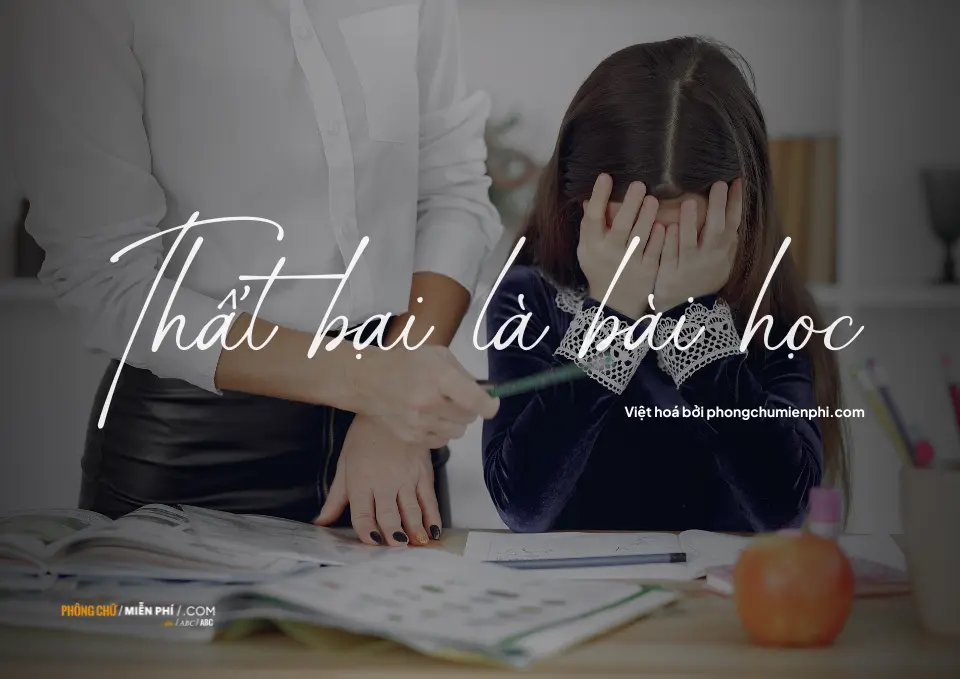
Tên font: Font Việt Hoá Gasthony Signature Script
Font Việt Hoá PCMP Gasthony Signature Script – Chữ ký tinh tế cho thiết kế sáng tạo
PCMP Gasthony Signature Script là một font chữ ký Việt Hoá mang phong cách viết tay tự nhiên, được phác thảo nhanh chóng trên giấy rồi số hoá thành định dạng vector sắc nét. Các đường nét uyển chuyển, mềm mại giúp font giữ được cảm giác chân thực như chữ ký thật, đồng thời vẫn đảm bảo tính thẩm mỹ cao trong mọi thiết kế.
Với phong cách script hiện đại, Gasthony Signature đặc biệt phù hợp cho nhiều nhu cầu sáng tạo:
Thiết kế thương hiệu & logo: tạo dấu ấn riêng biệt và chuyên nghiệp.
Thiệp cưới, thư mời & văn phòng phẩm: mang lại nét sang trọng, tinh tế.
Bài đăng mạng xã hội, quảng cáo & bao bì sản phẩm: nổi bật và thu hút ánh nhìn.
Nhãn mác, watermark & nhiếp ảnh: tăng tính nhận diện cá nhân hoặc doanh nghiệp.
Sự kiện đặc biệt: truyền tải cảm xúc một cách tinh tế.
Điểm nổi bật của PCMP Gasthony Signature Script
Việt hoá hoàn chỉnh hỗ trợ tiếng Việt đầy đủ.
Đường nét mềm mại, tự nhiên như chữ ký viết tay.
Ứng dụng đa dạng trong branding, thiết kế cá nhân và thương mại.